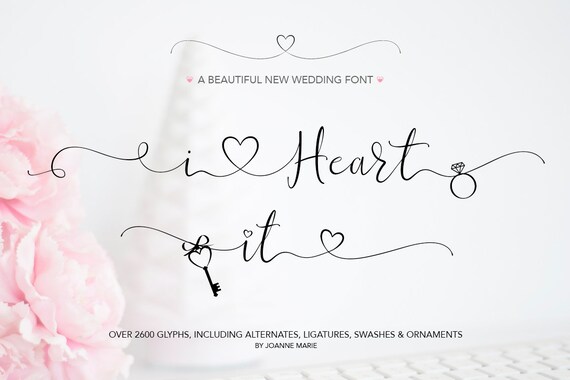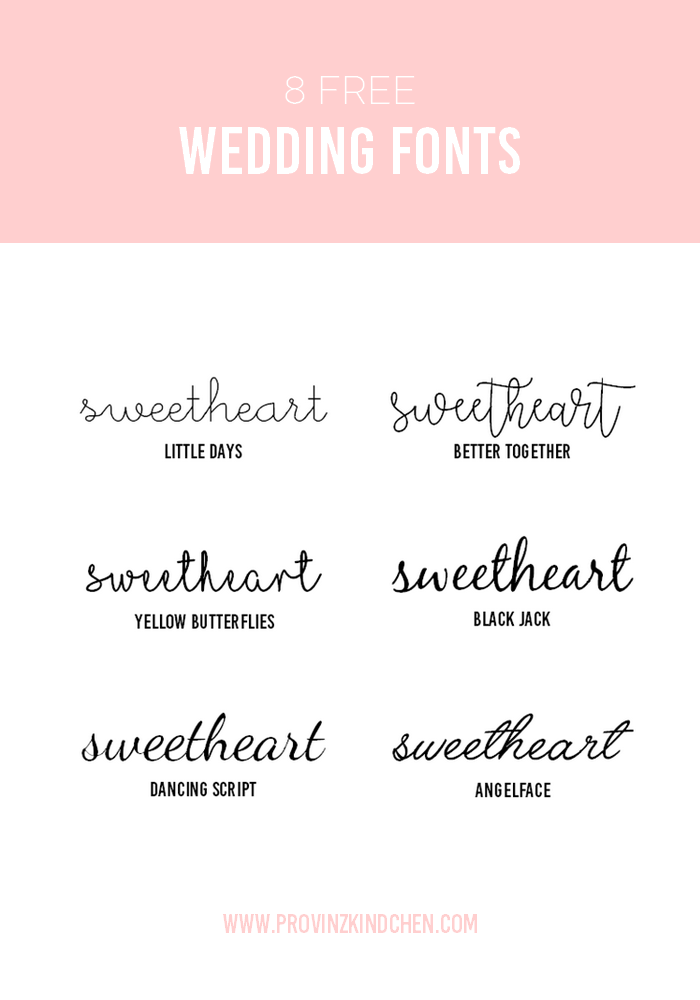
Schriftart Hochzeitseinladung
Wunderschöne kostenlose Schriftarten (free!) Als Überschrift eingesetzt sind handgeschriebene Schriftarten auch eine gute Wahl für Websites, die einen verspielten Look haben sollen #schriftartenhandschrift #schriftartenbuchstaben #schriftart #schriften #hochzeitspapeterie #hochzeitseinladung #branding #design #typografie #handschrift.
Schriftart hochzeitseinladung. First seen on DaFont January 17, 17 Illustration © Misti's Fonts Google Ads of Misti's Fonts. Font Meme is a fonts & typography resource The "Fonts in Use" section features posts about fonts used in logos, films, TV shows, video games, books and more;. DIY (also DoItYourself) ist die aktuelle TrendPhrase, wenn es um die Planung einer Hochzeit geht Viele Pärchen gestalten selbst Einladungskarten, DekoElemente und mehr, um eine individuelle Hochzeit zu feiern, die perfekt zu ihnen passtGenau deshalb haben wir hier 26 schöne Vorlagen für persönliche Hochzeitseinladungen zusammengesucht, die du nach Lust und Laune deinem Geschmack.
Und da dürfen die Einladungskarten natürlich nicht fehlen Ich nehme Euch bei dem ganzen Prozess mit Heute seht Ihr den ersten Teil, all m. WhatsApp Filmchen Hochzeitseinladung erfordert die Größe uff (berlinerisch) weniger als 16 MB und die Qualität des Videos sollte auch ziemlich gut sein Sofern Jene die Einladung bestizen professionell gedruckt, machen die Schlagzeile zeichnen sich anhand diese eine, Schriftart auswählen, die unterscheidet sich von jener Schriftart, die Sie. Mit eigenen Bildern, unterschiedlichen Schriftarten und Farben ist es kinderleicht, eine einzigartige Hochzeitseinladung zu erstellen Eine Hochzeit zu planen ist eine gewaltige Aufgabe Mit Canva kannst du einen Teil davon ganz leicht erledigen und wunderschöne Einladungen entwerfen, die deine Gäste begeistern werden.
Celebrate marriage with these beautiful modern calligraphy fonts We have the best collection of free wedding fonts!. Mit eigenen Bildern, unterschiedlichen Schriftarten und Farben ist es kinderleicht, eine einzigartige Hochzeitseinladung zu erstellen Eine Hochzeit zu planen ist eine gewaltige Aufgabe Mit Canva kannst du einen Teil davon ganz leicht erledigen und wunderschöne Einladungen entwerfen, die deine Gäste begeistern werden. Natürlich ist dann ein wenig “Handarbeit” angesagt Laden Sie doch Ihre Trauzeugen zum “basteln” ein – vielleicht in Kombination mit einem guten Abendessen oder einem Glas Wein?.
Zehn kostenlose Fonts für Einladungen, Menükarten und Co Bevor das JaWort vor Zeugen laut ausgesprochen wird, kommen so einige Vorbereitungen auf das zukünftige Brautpaar und deren Weddingplanner zu Für die Gestaltung individueller Hochzeitszeitungen, Menü oder Einladungskarten haben wir nun zehn ästhetische Schriftarten zusammengestellt. Erkunde Martina T Hallers Pinnwand „Hochzeitseinladungen“ auf Weitere Ideen zu einladungen, hochzeit, hochzeitseinladung. Egal für welche Hochzeitseinladung und Schriftarten ihr euch entscheidet, ihr werdet bestimmt eine passenden für euch als Paar finden In Canva findet ihr noch zahlreiche weitere EinladungsVorlagen und auch Schriftarten, falls oben keine passende dabei war.
The "Fonts Collection" section is the place where you can browse, filter, custom preview and. 0809 Erkunde Mareike Meyers Pinnwand „Kostenlose schriftarten“ auf Weitere Ideen zu kostenlose schriftarten, schrift. DIY (also DoItYourself) ist die aktuelle TrendPhrase, wenn es um die Planung einer Hochzeit geht Viele Pärchen gestalten selbst Einladungskarten, DekoElemente und mehr, um eine individuelle Hochzeit zu feiern, die perfekt zu ihnen passtGenau deshalb haben wir hier 26 schöne Vorlagen für persönliche Hochzeitseinladungen zusammengesucht, die du nach Lust und Laune deinem Geschmack.
The "Text Generator" section features simple tools that let you create graphics with fonts of different styles as well as various text effects;. Font Meme is a fonts & typography resource The "Fonts in Use" section features posts about fonts used in logos, films, TV shows, video games, books and more;. Das ist ne gute Frage, oder?.
Jener beste Nicht da, eine Hochzeitseinladung an das unverheiratetes Paar zu urteilen (nach), besteht darin, zwei Renommee gen den Warenumschlag über schreiben Einladung Schriftart Word Lesen Sie auch. Heute gibt's was Privates aus meiner kleinen Bastelwerkstatt 😊 Der Versuch, eine passende Schriftart für meinen #Adventskranz zu finden, ist kläglich gescheitert Also griff ich zu goldenem WashiTape und dünnem Basteldraht Et voila, der erste Teil des Kranzes steht Hochzeitseinladung Motiv Wimpel See All. NOTE This font is for PERSONAL USE ONLY!.